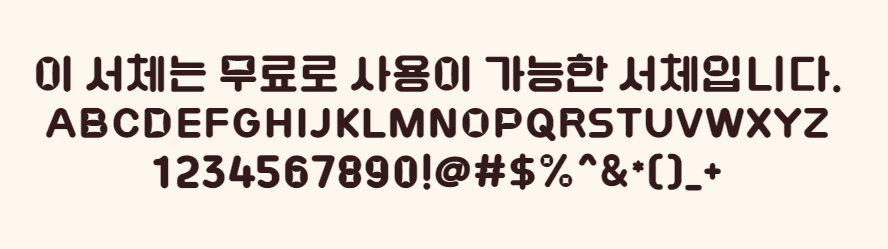
망고보드 별별체
폰트를 제작한 이유
망고보드 별별체는 디지털 콘텐츠 제작 플랫폼인 망고보드에서 사용자들이 다양한 디자인 작업을 수행할 때 활용할 수 있도록 개발한 서체입니다. 카드뉴스, 상세페이지, 홍보물, 동영상 등 다양한 콘텐츠를 제작할 때 일관된 디자인과 분위기를 유지하기 위해 자체적인 폰트를 제작하게 되었습니다. 이를 통해 사용자들이 통일된 브랜드 아이덴티티를 표현하고, 디자인 작업의 완성도를 높일 수 있도록 지원하고자 했습니다.
폰트 디자인의 특징
별별체는 별처럼 빛나는 느낌의 아이덴티티를 가진 서체로, 특정 초성에서 망고보드의 밝고 활기찬 모습을 볓빛 모양으로 표현하였습니다. 또한, 가로와 세로의 글자 비율을 1:1로 통일하여 안정감을 부여하였으며, 동글동글하고 통통한 느낌의 부드러운 모양을 가지고 있습니다. 이러한 디자인 요소들은 디자인의 주목도를 높여야 할 때 제목용 폰트로 활용하기에 적합합니다.
폰트 사용 용도
별별체는 다양한 디자인 작업에 활용할 수 있는 범용 서체입니다. 브로슈어, 포스터, 책, 잡지 등 인쇄물부터 웹페이지, 광고 배너, 이메일, 전자 브로슈어 등 디지털 콘텐츠까지 폭넓게 사용 가능합니다. 또한, 영상물의 자막이나 영화의 오프닝 및 엔딩 크레딧, UCC 등 영상 콘텐츠에도 활용할 수 있으며, 판매용 상품의 패키지 디자인이나 웹사이트 및 프로그램 서버 내 폰트 탑재, 전자책 제작 등 다양한 분야에서 활용할 수 있습니다.